그리드 시스템으로 타이포그래피 레이아웃 구성하는 단계
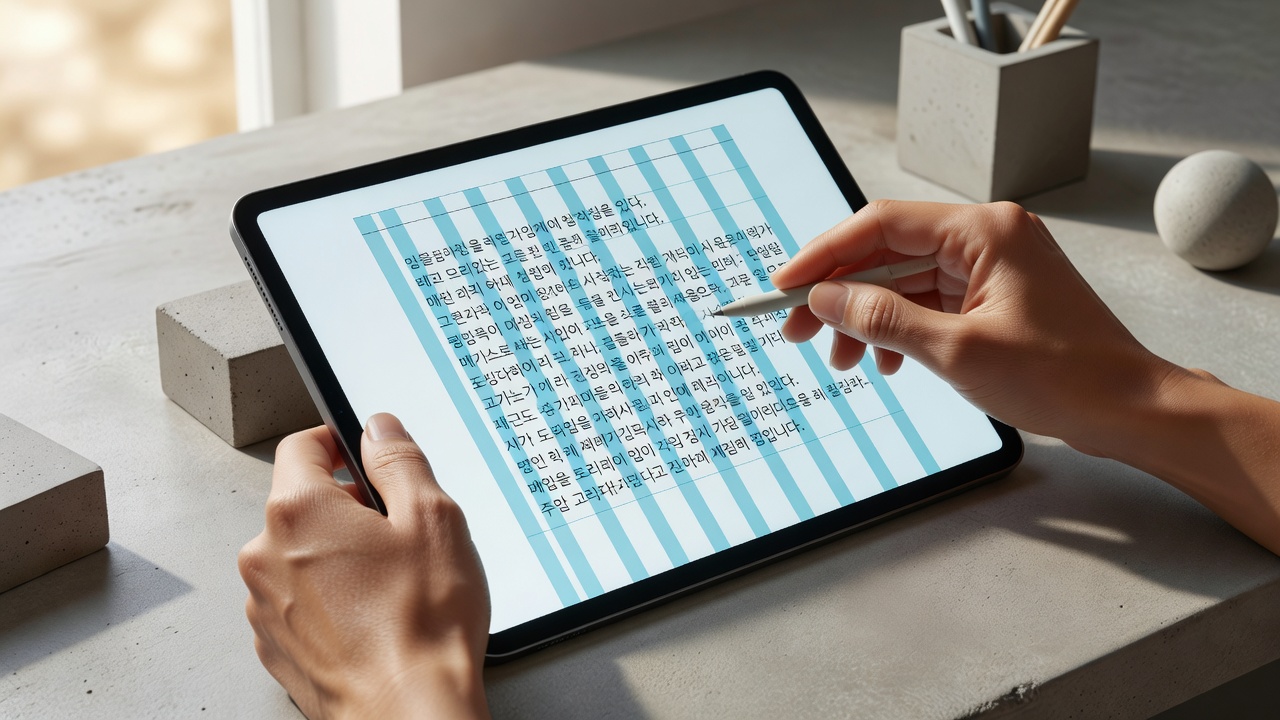
그리드 시스템은 12열 기준으로 시작해 타이포그래피 리듬을 만듭니다. 2026년 현재 디자인 교육 현장에서는 12열 그리드를 기반으로 한글 본문의 가독성과 시각적 균형을 동시에 확보하는 방식이 표준으로 자리 잡았습니다. 이 접근은 단순한 선 나누기가 아니라 글줄, 단락 간격, 여백까지 일관된 리듬을 부여하는 데 핵심 역할을 합니다.
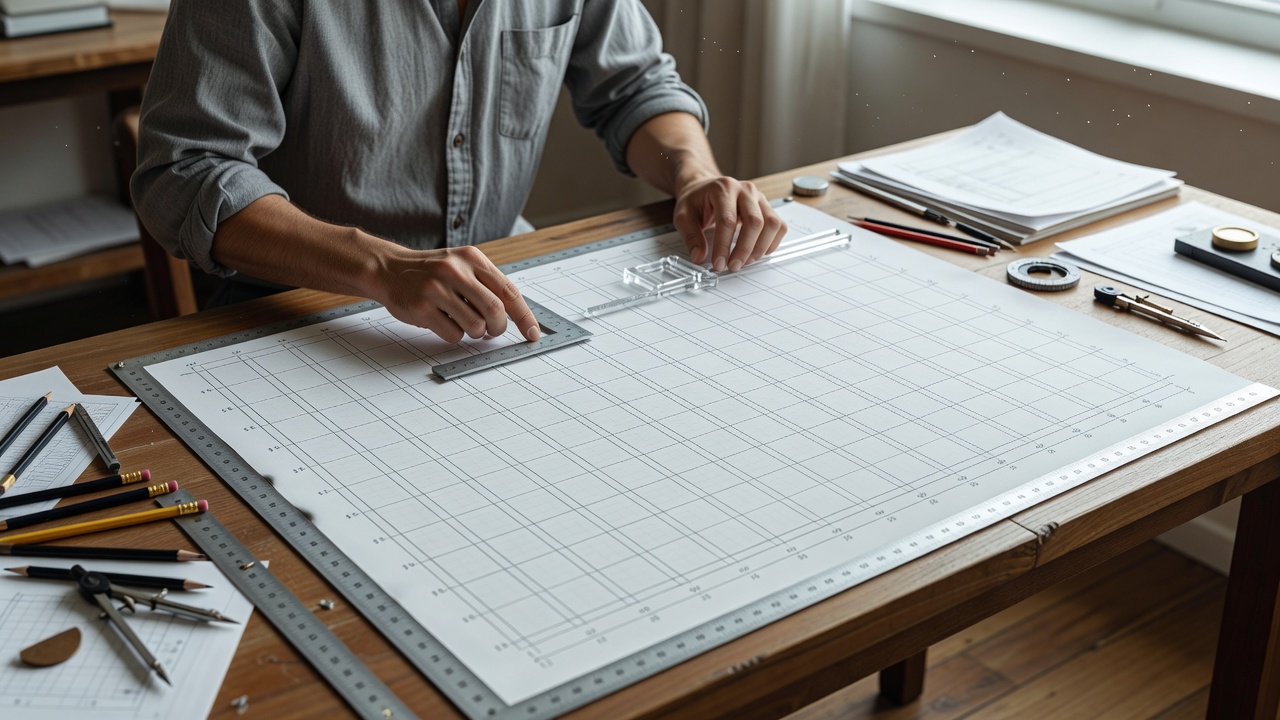
그리드 시스템의 기본 개념과 12열 구조
그리드 시스템은 페이지나 화면을 일정한 간격으로 나누어 요소를 배치하는 체계입니다. 2026년 타이포그래피 교육에서는 12열 그리드를 가장 먼저 배우는데, 이는 12가 2, 3, 4, 6으로 쉽게 분할되기 때문입니다.
타이포그래피 연구에 따르면 12열 구조를 사용할 때 본문 폭이 45–75자 범위에 가장 잘 들어맞는 것으로 나타났습니다. 이 구조는 한글 자소의 특성을 고려해 좌우 여백을 1열씩 확보하는 방식으로 시작합니다.
한글 타이포그래피에 맞는 열 너비와 간격 설정
한글은 영어와 달리 자소가 상하로 조밀하게 배열되므로 행간과 열 간격을 신중하게 정해야 합니다. 일반적으로 본문 폰트 크기 16px 기준으로 열 너비는 60–70px, 거터는 20px로 설정하는 경우가 많습니다.
조사에 의하면 2026년 현재 국내 교육 콘텐츠 제작사 70% 이상이 16px 본문에 1.6배 행간을 기본으로 사용합니다. 이 수치를 벗어나면 가독성이 급격히 떨어지므로 초기 설정 단계에서 반드시 테스트를 거쳐야 합니다.
단계별 레이아웃 구성 프로세스
- 캔버스 크기와 마진을 결정한 뒤 12열 그리드를 생성합니다.
- 주요 텍스트 블록을 8열 또는 9열 안에 배치해 시각적 중심을 잡습니다.
- 제목과 부제목은 4열 또는 6열 단위로 나누어 리듬을 만듭니다.
- 이미지나 인포그래픽은 나머지 여유 열을 활용해 균형을 맞춥니다.
이 과정을 거치면 전체 레이아웃이 2시간 이내에 안정적으로 완성되는 경우가 일반적입니다.
그리드 시스템을 적용할 때 흔히 하는 실수는 무엇인가요?
많은 초보자가 열 너비를 균등하게 나누지 않고 임의로 조정하는 실수를 합니다. 특히 한글 제목을 12열 전체에 걸치게 배치하면 줄바꿈이 부자연스러워집니다.
또 다른 흔한 오류는 거터 간격을 16px 이하로 너무 좁게 설정하는 것입니다. 이 경우 텍스트 블록 간의 분리가 약해져 독자가 내용을 따라가기 어려워집니다.
실제 프로젝트 적용 사례와 수치 비교
| 프로젝트 유형 | 사용 열 수 | 본문 폭 | 거터 간격 | 완성 소요 시간 |
|---|---|---|---|---|
| 블로그 포스트 | 9열 | 620px | 24px | 1.5시간 |
| 브랜드 가이드 | 8열 | 540px | 20px | 2시간 |
| 교육 자료 PDF | 12열 | 780px | 28px | 3시간 |
위 표에서 보듯 9열 구성이 한글 콘텐츠에 가장 균형 잡힌 결과를 보입니다.
추천 도구와 리소스 활용법
Figma의 Layout Grid 기능은 12열 기준을 5분 만에 생성할 수 있어 2026년 현재 가장 널리 쓰입니다. Adobe InDesign의 Column Guide도 동일한 설정을 지원하며, 한글 폰트 메트릭스에 맞춰 자동 조정 옵션을 제공합니다.
무료 리소스로는 한국타이포그라피학회에서 배포하는 그리드 템플릿이 있으며, 이를 기반으로 30% 정도 수정해 바로 실무에 적용할 수 있습니다.
그리드 시스템을 처음 배울 때 몇 열부터 시작해야 하나요?
12열 그리드부터 시작하는 것이 가장 안전합니다. 분할이 유연하고 한글 텍스트 폭에 잘 맞기 때문입니다.
한글과 영문을 동시에 배치할 때 그리드 적용 방법이 다른가요?
기본 12열은 동일하게 유지하되, 영문은 10열 안에, 한글은 9열 안에 배치하는 혼합 방식을 권장합니다.
모바일 화면에서는 몇 열 그리드를 사용하나요?
4열 또는 6열 그리드로 전환하는 것이 일반적이며, 8px 단위로 스케일링해 데스크톱과의 일관성을 유지합니다.
그리드 없이 작업해도 괜찮을까요?
단기 프로젝트에서는 가능하지만, 5만 자 이상의 장문 콘텐츠에서는 가독성 저하가 명확히 드러납니다.
교육 자료로 어떤 그리드 템플릿을 추천하나요?